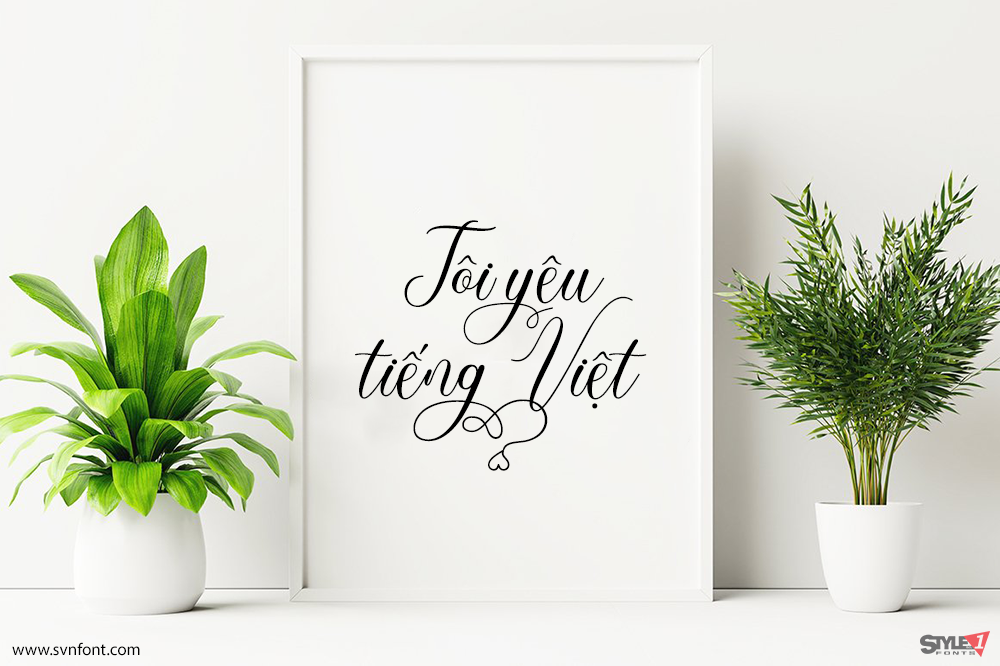
Waliglona là một font script đẹp mắt với nhiều kiểu thay thế (alternate styles), mang vẻ tự nhiên, thanh lịch và rất phù hợp cho những dự án độc đáo, nổi bật.
Font thích hợp cho nhiều ứng dụng như thiệp mời, bao bì sản phẩm, ưu đãi/quảng cáo, thiết kế sản phẩm, đồ thủ công, nhãn mác, nhiếp ảnh, watermark, logo và branding.
Nhà thiết kế: Ikhsan Maulana